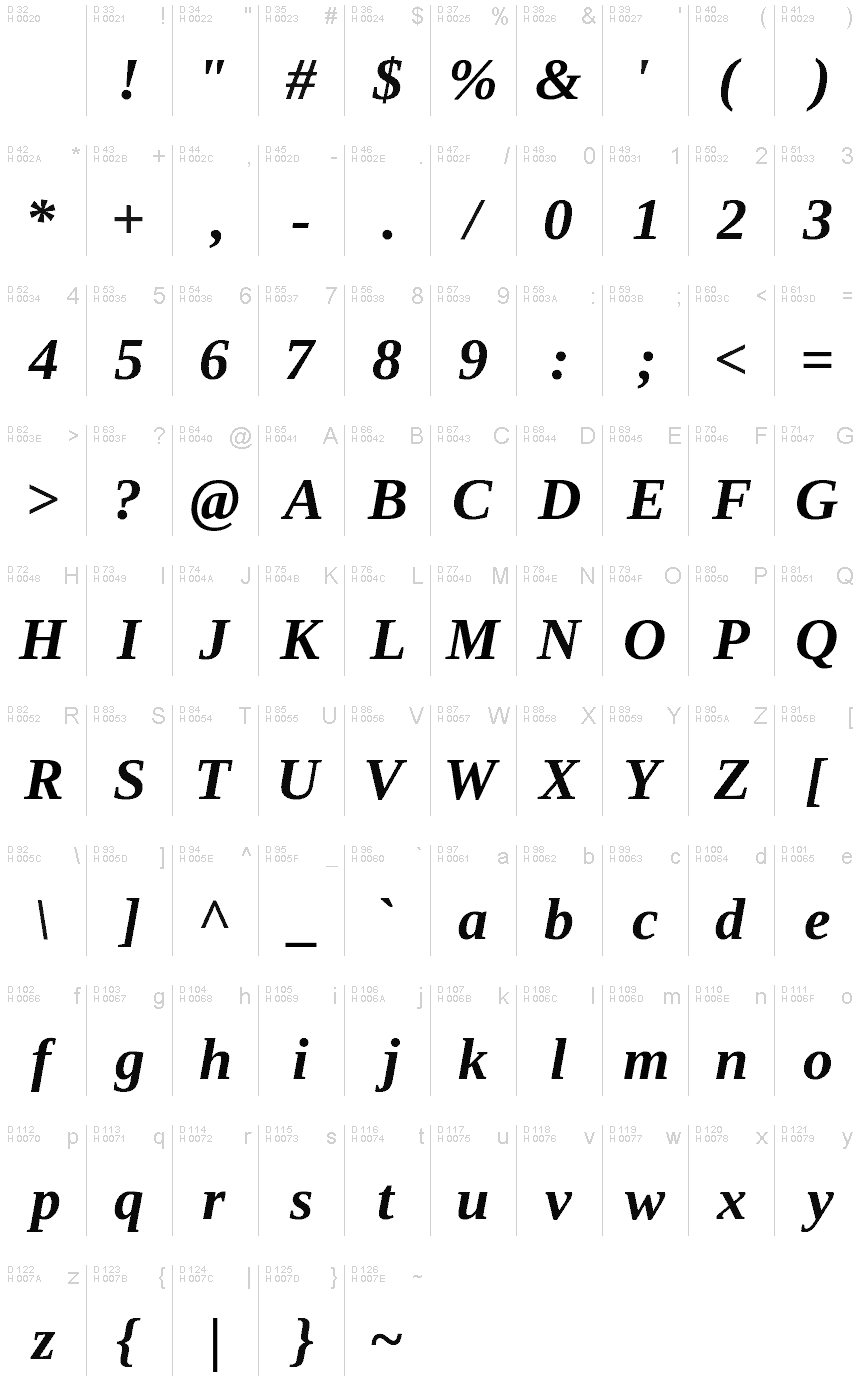
Liberation Serif Bold Italic, un font serif corsivo gratuito di Ascender Corporation, possiede il tono familiare dei caratteri da giornale e da libro di stampo transizionale, spinto però verso un'inclinazione più vivace ed enfatica. Le lettere appaiono ampie e sicure piuttosto che delicate, con grazie a cuneo, forme minuscole arrotondate e una spiccata inclinazione in avanti che conferisce al font una voce formale, ma sempre in movimento.
Questo mix è ideale per titoli editoriali, copertine di riviste, titoli di report, citazioni e testi di packaging in cui si desidera l'autorità classica di un carattere serif con un tocco di dinamismo in più. Trattandosi di un font gratuito, è perfetto anche per poster e cartelli, specialmente quando si vuole infondere a poche parole il fascino della stampa d'altri tempi senza risultare rigidi.